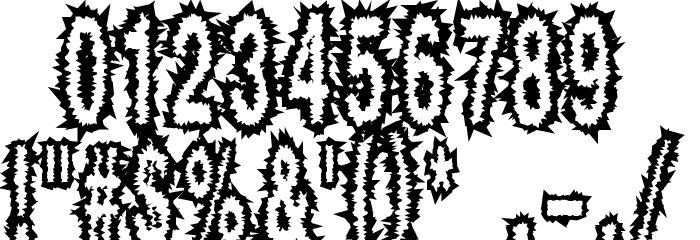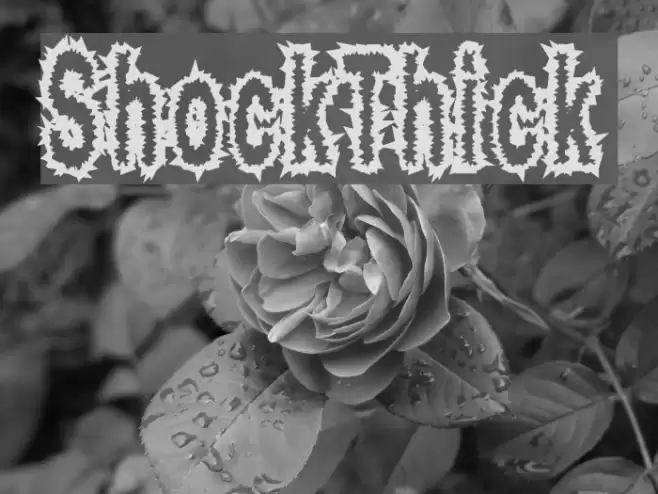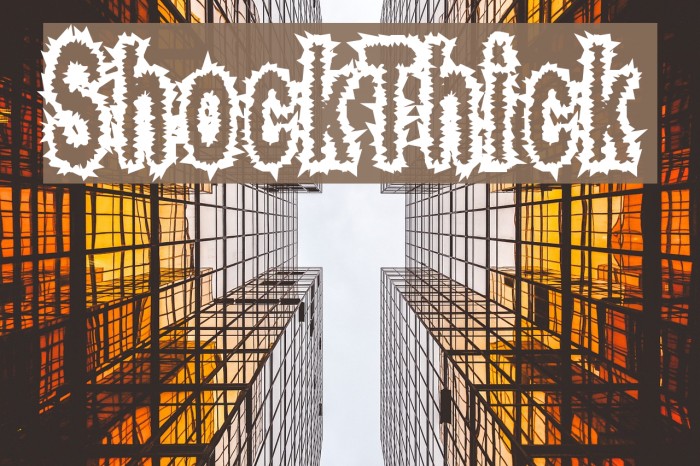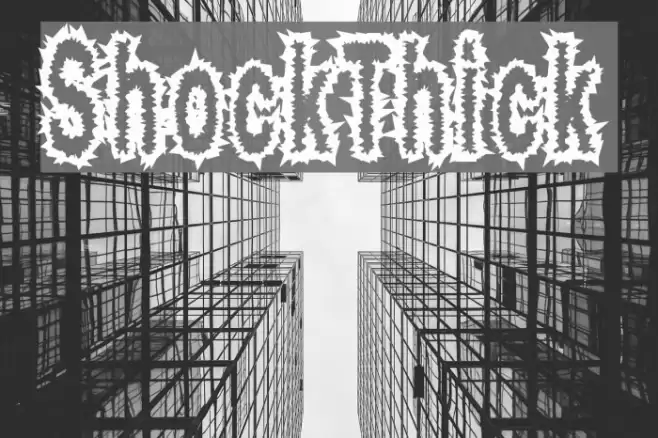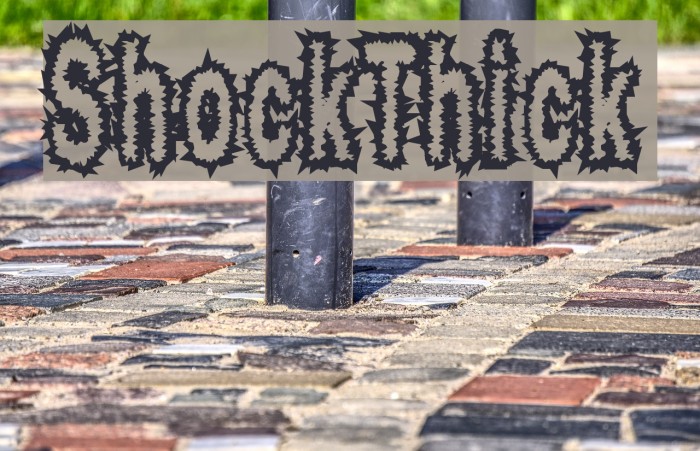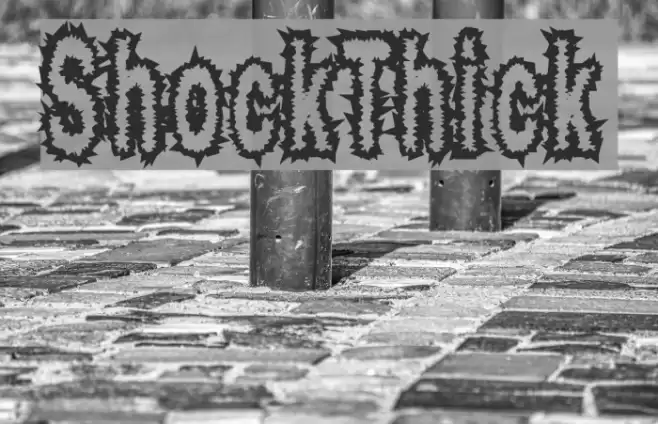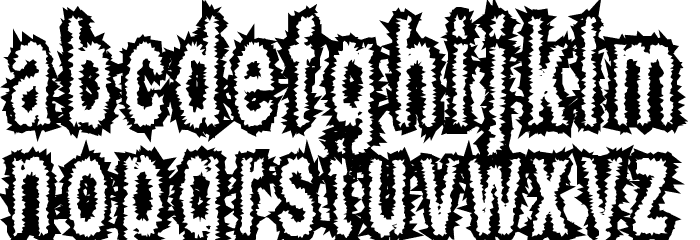
ShockThick Font
✎ Distorted Eroded
| おすすめプロジェクト | Ideal for Halloween-themed designs, comic book titles, event posters, or any project needing a dramatic and energetic typeface. |